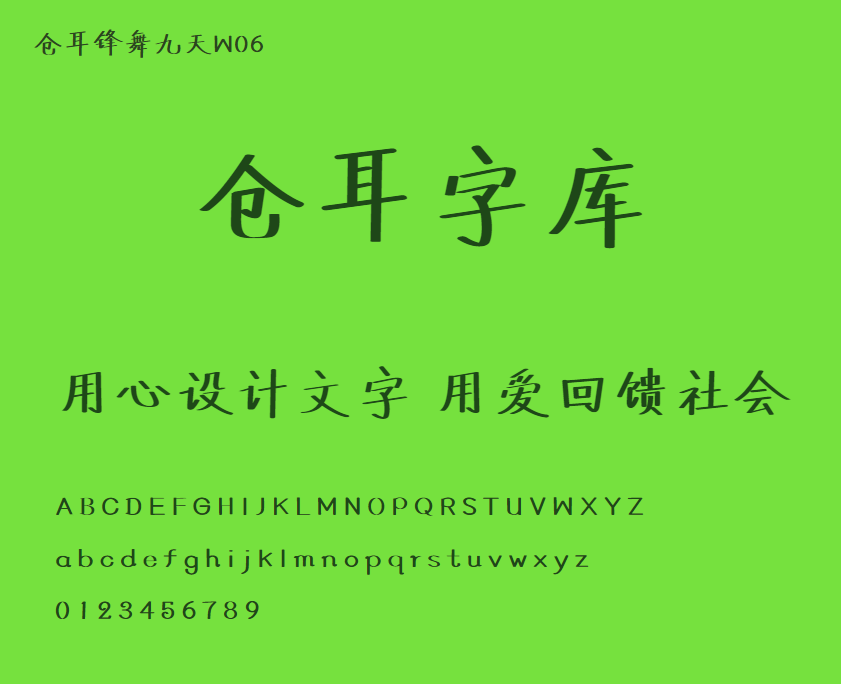
仓耳锋舞九天W06
仓耳锋舞九天W06,这款字体结构工整、笔画清晰,兼顾美观与易读性,适用于标题、正文、海报、包装、LOGO 等多种场景。字形优雅稳定,风格百搭耐看,适配日常排版与创意设计,让文字呈现更舒适、更具质感。仓耳锋舞九天W06一笔一画,皆是细节,以均衡的比例、流畅的线条打造舒适视觉体验,字形端正大气,风格简约现代。无论是商业设计、品牌宣传还是日常排版,都能轻松驾驭,让文字更有格调与力量。仓耳锋舞九天W06字体下载。